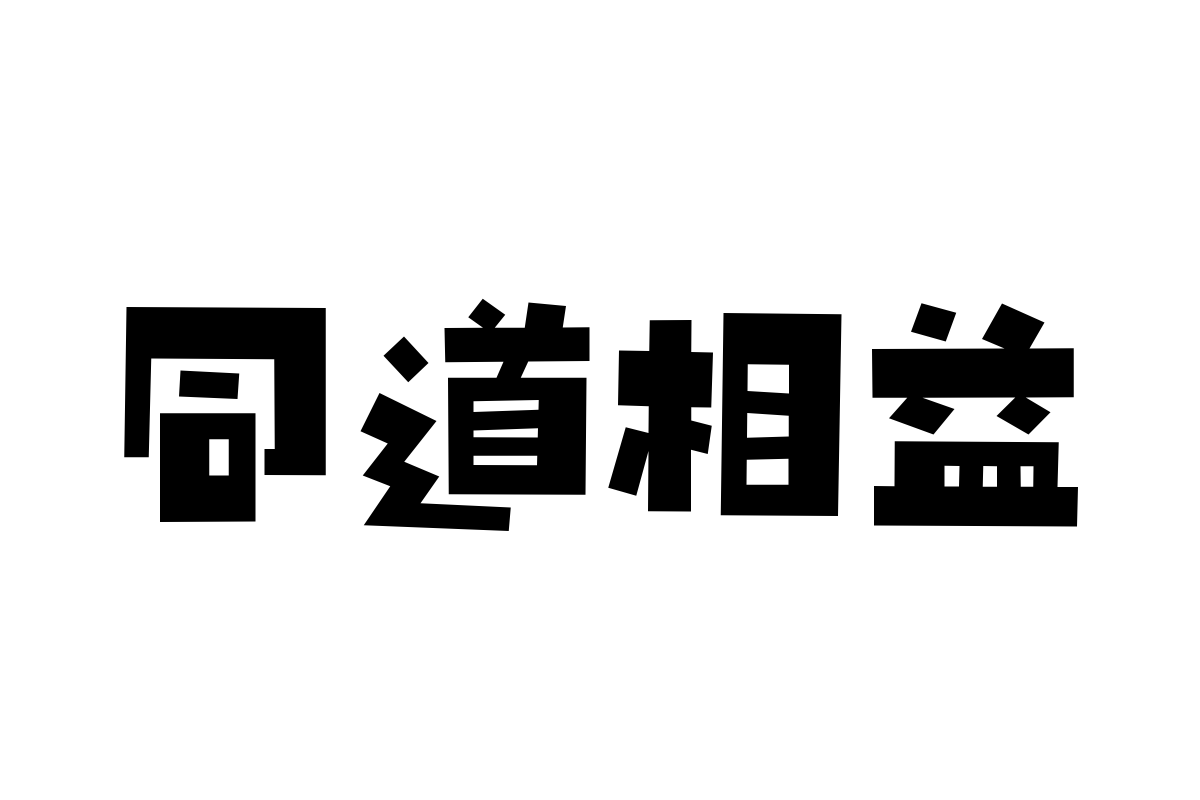
汉仪铸字方脑壳是一款由汉仪公司设计的中文字体,具有独特的方形设计。这款字体适用于各种印刷品和数字媒体,如书籍、杂志、报纸、海报、广告、网页等。
汉仪铸字方脑壳的特点如下:
1. 字形独特:该字体采用方形设计,线条简洁明了,易于识别。
2. 风格统一:无论是在印刷品还是数字媒体上,汉仪铸字方脑壳都能保持整体风格的一致性。
3. 适用范围广泛:适用于各种印刷品和数字媒体,如书籍、杂志、报纸、海报、广告、网页等。
总之,汉仪铸字方脑壳是一款功能强大、适应性强的中文字体,适用于各种印刷品和数字媒体的设计需求。